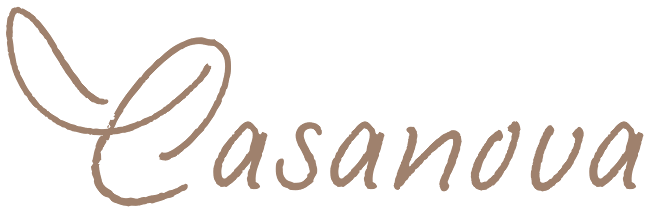
Ich such einen Ersatz für die Angelina, die leider keine Umlaute hat …
Angelina:
"Wiesbaden Swing" käme schon ganz gut hin, ist aber im Vergleich ein wenig zu eckig.
Gerne auch andere Vorschläge für eine schöne, runde, weibliche Handschrift :-)
Die hat mich als erstes an die Casanova Script erinnert – ob’s ’ne Alternative für dich ist, weiß ich aber nicht ...
Die Casanova finde ich nicht weiblich genug …  :roll:
für was suchst du denn die schrift, mengentext?
die wendy find ich sehr weiblich und ansprechend ist aber für längere texte nicht geeignet.
das t ist auch sehr amerikanisch.
An die Bradley habe ich auch gedacht. Die Bradley Hand ITC würde nix kosten  :-)
für was suchst du denn die schrift, mengentext?
Das ist nur wenig Text, Aufzählung mit 3 Punkten, die eine Frauenhand in der Hand hält.
An die Bradley habe ich auch gedacht. Die Bradley Hand ITC würde nix kosten  :-)
Die Bradley ist toll, danke euch :-) Aber: Ist dieser fontzone-link legal? Ich hab da meine Zweifel, dass ein Font von ITC einfach so kostenlos ist … Die Bradley Hand ITC hab ich sogar auf meinem Rechner, die ist auch wesentlich fetter als die in deinem link.
Rollerscript ist toll, die muss ich mir als männliche Handschrift merken :-)